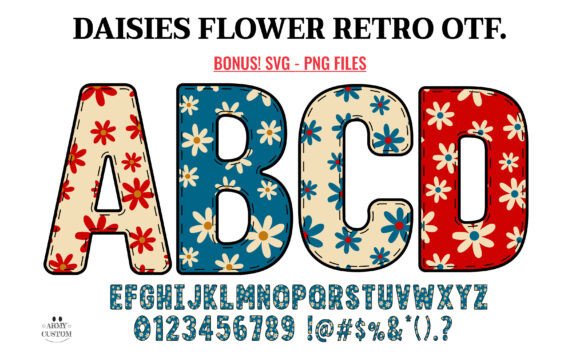
Daisy Flower Retro Bundle
Encontrar los elementos de diseño adecuados puede ser un desafío, pero Daisy Flower Retro Bundle ofrece una colección excepcional que eleva tu trabajo al instante.
Elaborado con precisión, Daisy Flower Retro Bundle proporciona vectores limpios, tipografía suave y una licencia comercial para tu tranquilidad.